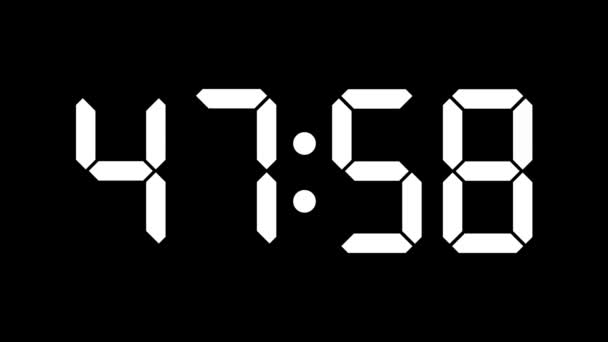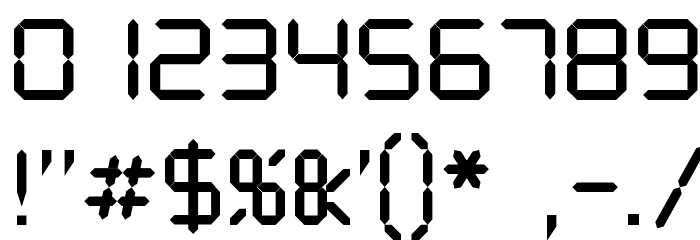
Шрифт электронных часов
У когонибудь есть или подскажите как называется ttf-шрифт как в электронных часах цыфры? Я нашел 2 шрифта: DS Crystal и a_LCDNova, но мне они не понравились… в первом единица как семерка такое ощущение, а во втором много «палочек»… вот есть попроще у когонибудь шрифт электронных часов? чтобы например таже единица была просто прямой… ну как обычно в часах )))
НЕ могу подсказать название, но если поставить корел, там таких шрифтов — масса
TStas © (22.03.06 14:49) [1]
НЕ могу подсказать название, но если поставить корел, там таких шрифтов — масса
ну, не совсем масса… точнее, под LCD-шрифт нет вообще (Корел 11)
Kolan © (2006-03-22 16:08) [5]
У меня стоит Corel 12 и нет там таких шрифтов…
>Дмитрий_177 Вот к сожалению 10 не желает в ХР ставится или диск битый, не ззнаю точно
11 Корел под ХР свтает точно и фрифты там ttf
>В самом — да.
ОН их в папку fonts пишиет. ПОставил Корел, около 100 шрифтов прибавилось. Откуда?
Как изменить размер шрифта
Размер с помощью настроек телефона позволяют изменить все производители. Сделать это очень легко. Достаточно зайти в настройки телефона или планшета и выбрать подпункт меню «Дисплей». В нем кроме общих настроек находится возможность изменить размер шрифта от маленького до очень большого.
Внесение изменений в шрифт 10 через пользовательский интерфейс — самый простой способ того, как изменить стиль шрифта на «Андроид», позволяющий изменить все его характеристики, включая размер, форму и даже прозрачность через настройки телефона.
Существует множество возможностей без получения root-прав внести изменения в облик программного обеспечения вашего планшета или смартфона. Среди них больше всего возможностей у владельцев азиатских телефонов. Для них доступен выбор из предустановленных шрифтов в настройках. Для всех остальных вопрос изменения оформления устройства без рут-прав решается через установку тем или лаунчера из Play Market.
Меню настроек
Как изменить шрифт на «Андроиде» с помощью меню настроек? Мобильные гаджеты, выпущенные Samsung и LG и некоторыми китайскими производителями, уже имеют встроенный в основную прошивку выбор альтернативных вариантов отображения текста.
Для их владельцев все очень просто:
- Зайдите в настройки.
- В разделе «Устройство» зайдите в «Дисплей».
- Кликните подпункт «Шрифт» и выберите себе понравившийся по написанию.
Если не понравился ни один из предустановленных шрифтов, вы можете найти подходящие в магазине приложений Samsung.
Если отображается окно предупреждения, прочтите и подтвердите, что перечисленные функции и компоненты не могут использоваться при использовании этого компонента типа погоды. Нажмите ОК .
Поместите погодный компонент на циферблат, перетащив его в нужное место.
В разделе «Внешний вид» окна «Свойства»:
а. Выберите Bitmap Font , затем нажмите Bitmap Font Setting .
г. На вкладке Custom выберите Добавить текстовую строку и введите основной тип отображения (на английском языке). Повторите этот шаг для каждого типа основного дисплея.